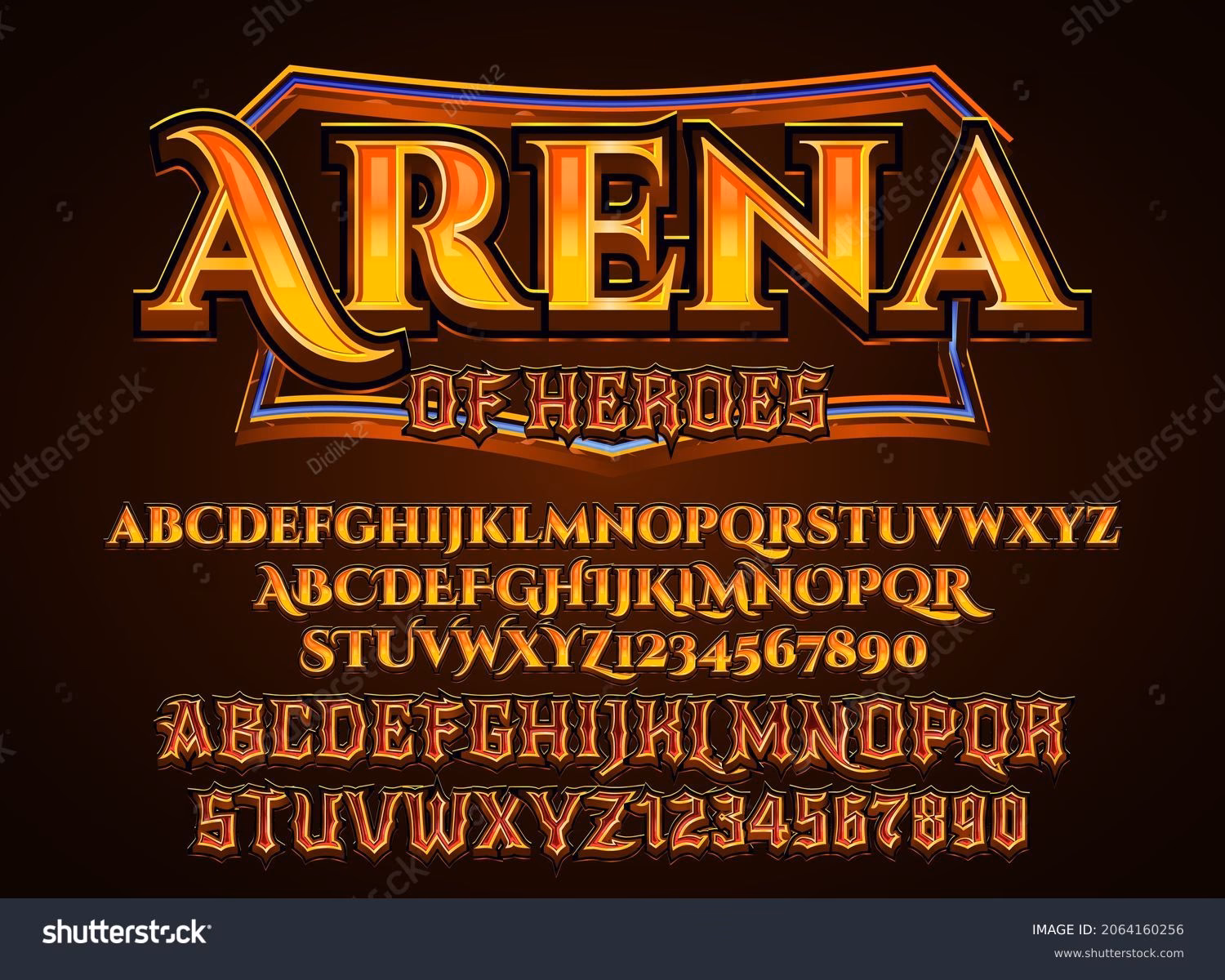
Skrifttyper er mere end bare bogstaver; de er en fundamental del af visuel kommunikation. Ligesom et fotografi vælger sit motiv og komposition for at fortælle en historie, vælger en designer en skrifttype for at formidle en følelse, en tone og en specifik besked. Valget af den rigtige skrifttype kan øjeblikkeligt sætte stemningen for et projekt, hvad enten det er et spændende eventyr, et dybt rollespil, en fængslende annonce eller et tydeligt skilt. Forståelse for typografi er lige så vigtig for en visuel skaber som at mestre kameraets indstillinger eller kompositionens principper.
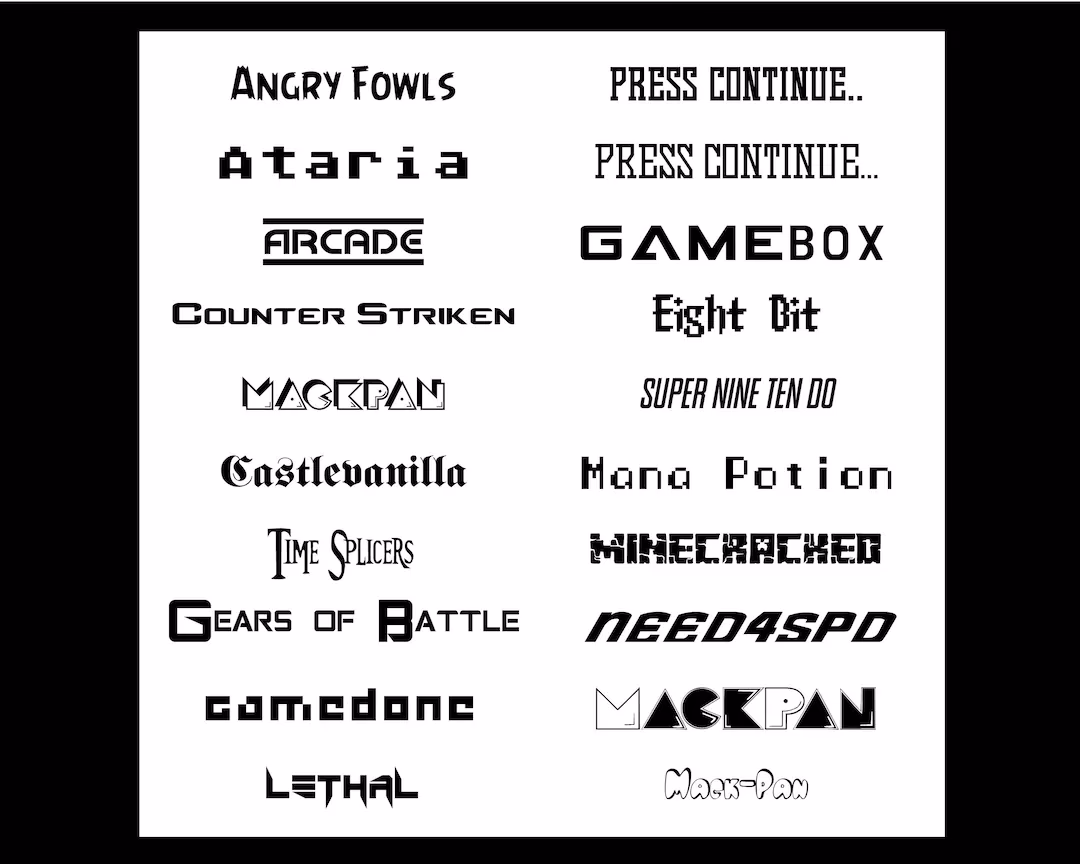
Skrifttyper til Eventyr og Opdagelse
Når vi tænker på eventyr, tænker vi på rejser, ukendte steder, spænding og robusthed. Skrifttyper, der passer til dette tema, har ofte en følelse af bevægelse, håndlavet kvalitet eller en vis råhed. De skal indgyde en følelse af nysgerrighed, opdagelse og verden, der venter på at blive udforsket. Disse skrifttyper kan bruges til titler på rejseblogs, bogomslag om ekspeditioner, branding for udendørsudstyr, eller som elementer i spil, der foregår i vildmarken.
Her er nogle eksempler på skrifttyper, der fanger essensen af eventyr:
- Wanderlust - Travel Font: Navnet alene antyder rejse og en længsel efter at udforske.
- Boomba: Kan have et energisk og lidt uforudsigeligt udtryk, der passer til uventede eventyr.
- Pocky Block: Kan give en legende, men solid fornemmelse, som en gammel træhytte i skoven.
- Retrican - Retro Sans Font: En følelse af nostalgi og klassisk udforskning, måske som en gammel ekspeditionsrapport.
- Elbrush Signation Font Duo: Kan tilbyde en personlig, håndskrevet følelse, som noter fra en rejsedagbog.
- Power of Dragon Typeface: Tyder på fantasy eller episke fortællinger og mytiske eventyr.
- The Great Outdoors: Perfekt til temaer om natur, camping, vandring og udendørs aktiviteter.
- Palmera - Geometric Slab Serif: Kan føles solid, pålidelig og jordnær, som en gammel, slidt læderbog.
Valget afhænger af den specifikke type eventyr – en tropisk rejse kræver måske noget andet end en arktisk ekspedition eller et fantasy-quest, men disse eksempler giver et godt udgangspunkt for at finde den rette tone.
Skrifttypernes Afgørende Rolle i RPG Spil
I rollespil (RPG) er skrifttypen ikke bare tekst; den er en integreret del af spillets verden og atmosfære. Når designere vælger skrifttyper til et spil, tager de et stort ansvar for den visuelle identitet, temaet og stemningen. Tænk på den dramatiske forskel: et gyserspil bruger ofte uhyggelige, forvrængede eller knap læselige skrifttyper for at skabe en følelse af ubehag og fare, mens et fantasyspil typisk vælger udsmykkede, elegante eller runelignende skrifttyper for at fremkalde en magisk eller episk atmosfære.
Spillere har ofte dybtliggende forventninger til en spilgenre – forventninger formet af utallige timer brugt på at læse fantasybøger, se sci-fi-film eller spille tidligere spil i genren. Den korrekte skrifttype kan øjeblikkeligt transportere spillere ind i spillets verden, fordybe dem i fortællingen og gøre deres spiloplevelse langt rigere. Skrifttyper er derfor en kritisk komponent i spildesign, der signifikant påvirker brugeroplevelsen, ikke kun i den lange tekst i spillet (dialog, beskrivelser) men også i spillets logo og menuer.
Valget af skrifttype til et RPG skal overveje både æstetik og funktionalitet. Teksten skal være læsbar, især i lange passager, men den skal også visuelt understøtte spillets tema. En for "kedelig" eller generisk skrifttype kan bryde illusionen, mens en for "overgjort" skrifttype kan gøre teksten svær at læse. Det handler om at finde den perfekte balance, der både er stemningsfuld og praktisk.
De Mest Iøjnefaldende Skrifttyper til Annoncering
Annoncering og skiltning har et primært mål: at fange opmærksomhed og hurtigt formidle et budskab. Skrifttyper, der bruges her, skal være yderst effektive til at opnå dette. De skal ikke kun være æstetisk tiltalende, men frem for alt have høj læsbarhed og evnen til at skille sig ud. Valget af skrifttype er afgørende for succesfulde marketingkampagner, da det hjælper med at formidle brandets budskab, sætte den rette tone og fange målgruppens opmærksomhed, uanset om det er på et fysisk skilt eller i digital annoncering.
Faktorer som bogstavafstand (kerning og tracking), størrelse, vægt og farvekontrast er alle vigtige for skiltningens og annoncens samlede effektivitet. Her er nogle af de mest iøjnefaldende og populære skrifttyper til annoncering:
- Helvetica: En sand klassiker. Neutralt og tidløst udseende, yderst læsbar selv i små størrelser eller på afstand. Minimalistisk design, der lader budskabet træde frem. Alsidig for alle medier.
- Bodoni Moda: En moderne serif med skarpe, rene linjer og høj kontrast mellem tykke og tynde strøg. Elegant og tidløs, ofte brugt af high-end brands eller produkter. Virker utroligt stærkt i store størrelser.
- Trajan: Baseret på letterforms fra antikke romerske inskriptioner. Giver et tidløst og sofistikeret look. Dens fede og stærke former gør den yderst synlig og læsbar på afstand, ideel til store formater som billboards.